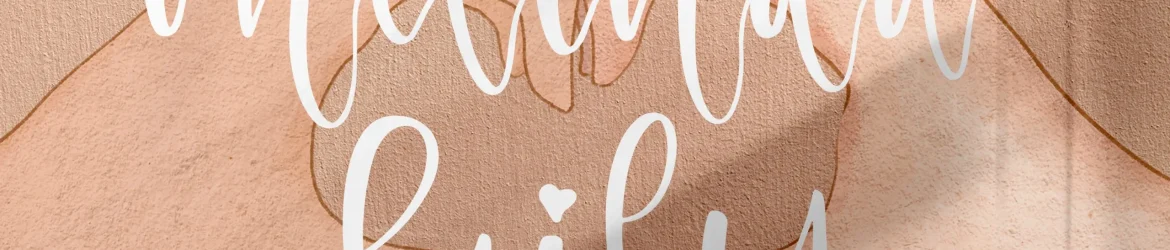
Melinda Daily Font – Download Grátis
Nossa nova adição à família das fuentes Calligraphy é a ‘Melinda Daily Font’, uma elegante escolha para qualquer projeto que precisa de uma pitada de beleza na tipografia. Fornecida pelo designer perspectype, esta font se destaca por seu charme romântico, sendo ideal para diversos tipos de projetos gráficos. A ‘Melinda’ é perfeita para os logos e as marcas que precisam de um toque delicado; adequada também para identificar a sua marca em produtos como embalagens, sacolas de viagem ou até mesmo na capa de seu livro favorito. Para aqueles que desejam dar um tom pessoal à sua coleção de mug, ou para quem busca uma frase motivacional no papel da sua t-shirt, a ‘Melinda’ tem o toque ideal. Não importa qual seja o projeto: desde criações do design de interiores até cartões de aniversário e adesivos, tudo beneficiará do encanto elegante dessa font. Ela também se destaca quando se trata das etiquetas dos seus produtos ou nas imagens onde você deseja uma mistura suave entre texto e fotografia. A ‘Melinda’ é a escolha perfeita para todos aqueles momentos especiais, como eventos de casamento ou simplesmente para dar um toque final ao seu trabalho artístico. A ‘Melinda Daily Font’, assim, não apenas completa o seu projeto com uma pitada de sofisticação, mas também o enriquece com um brilho único e personalizado. Seja você um designer profissional ou simplesmente alguém que cria coisas para se divertir, a ‘Melinda’ é definitivamente a fonte perfeita.